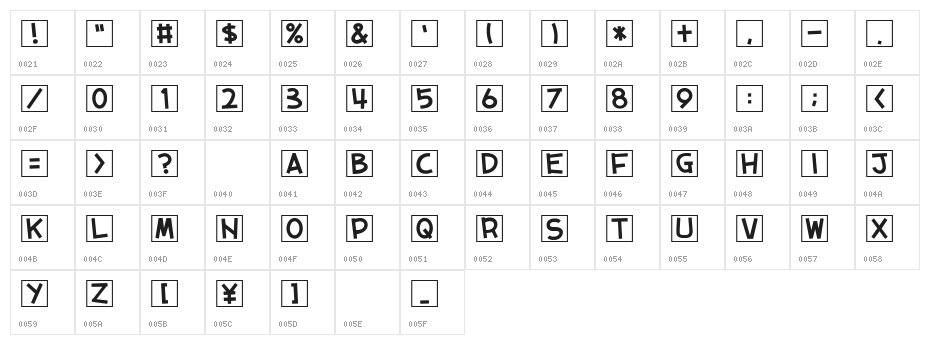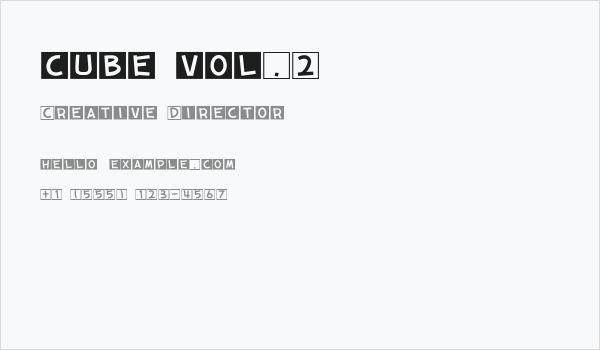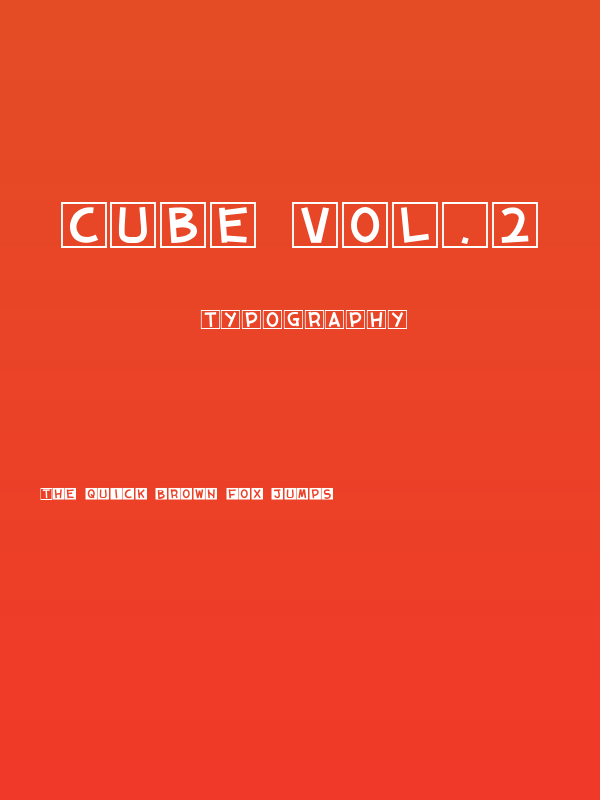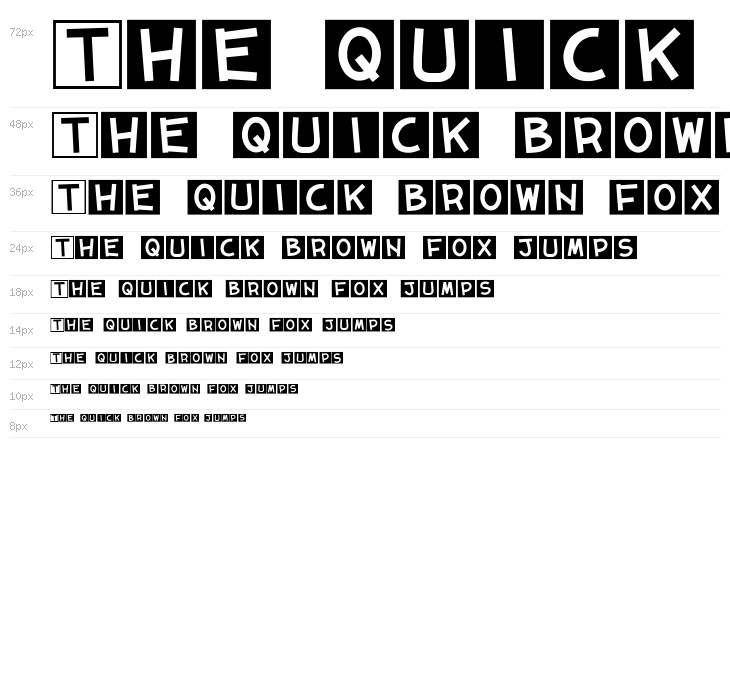
cube vol.2 Font
| Gesamtstil | Playful, Fun |
| Vorgeschlagene Projekte | Ideal for children's books, educational materials, playful branding, and creative posters. |